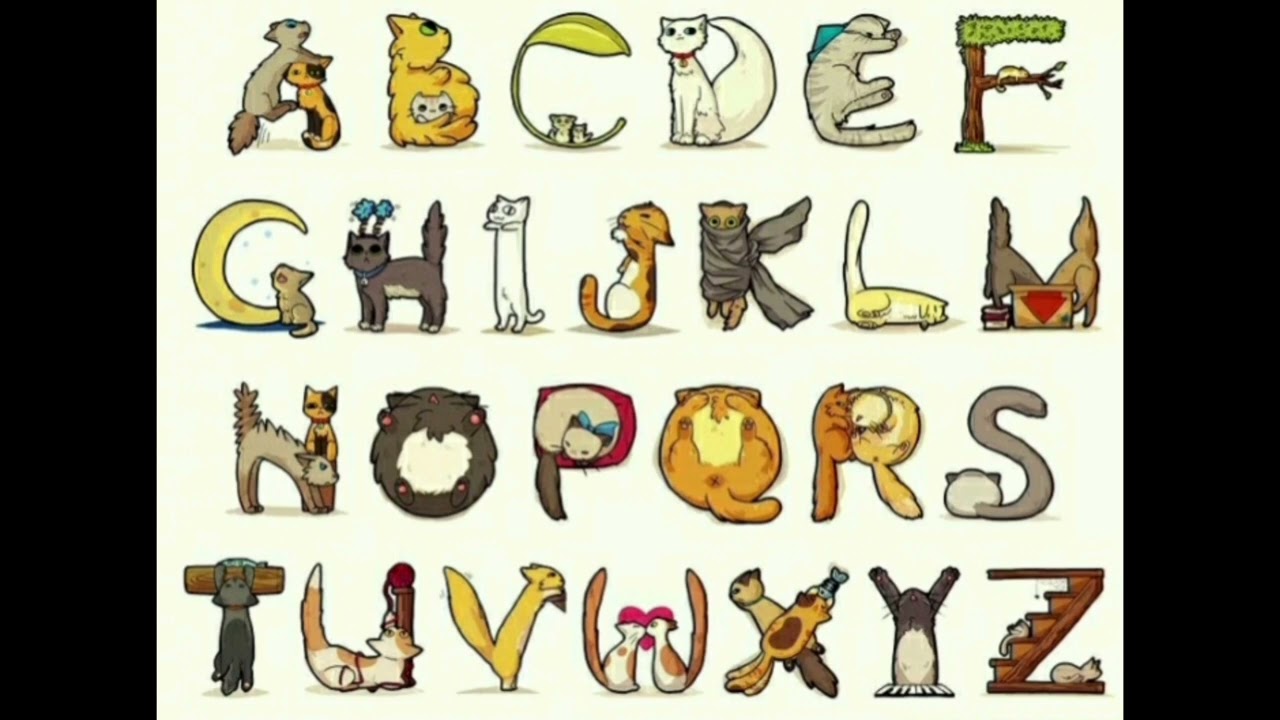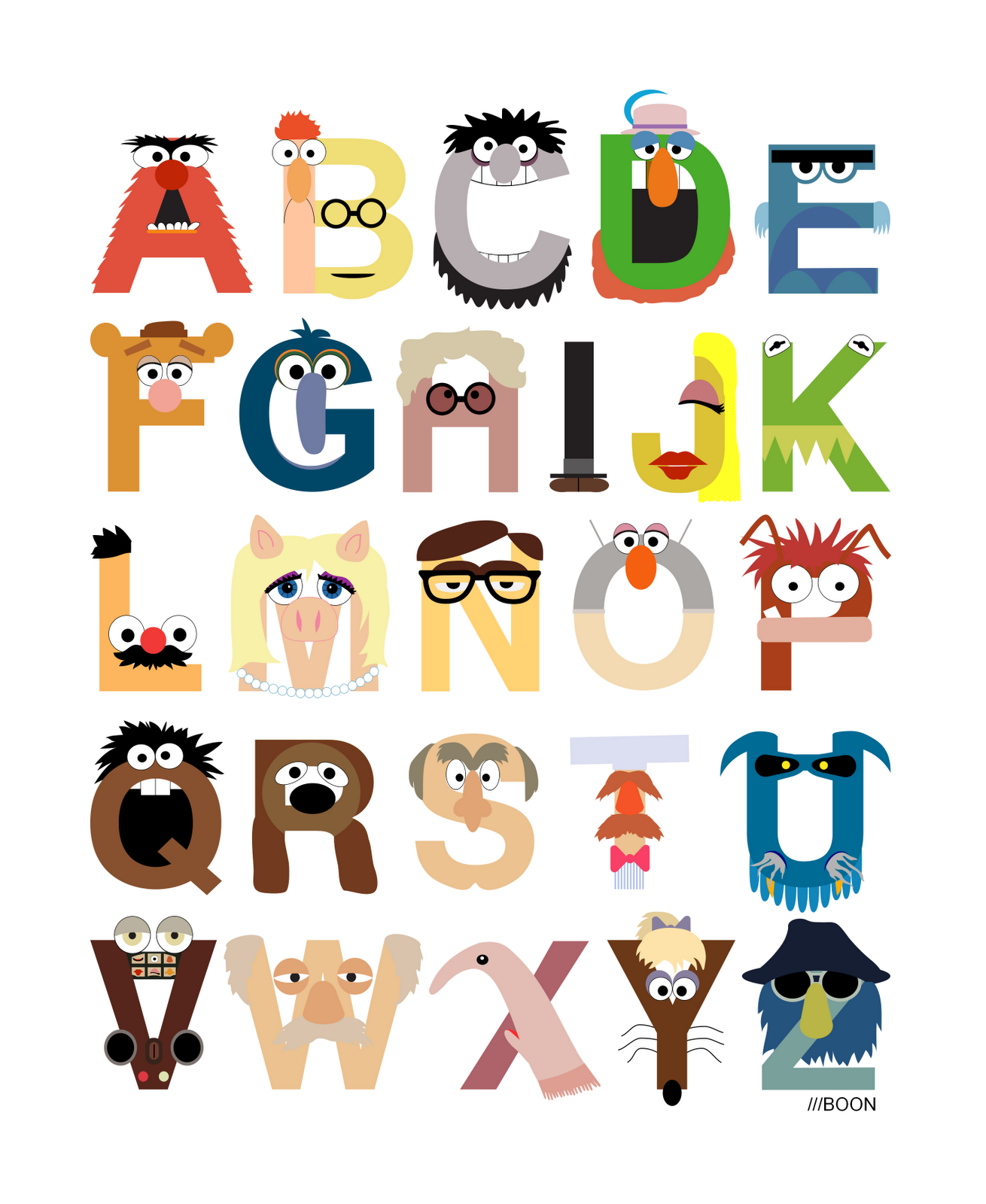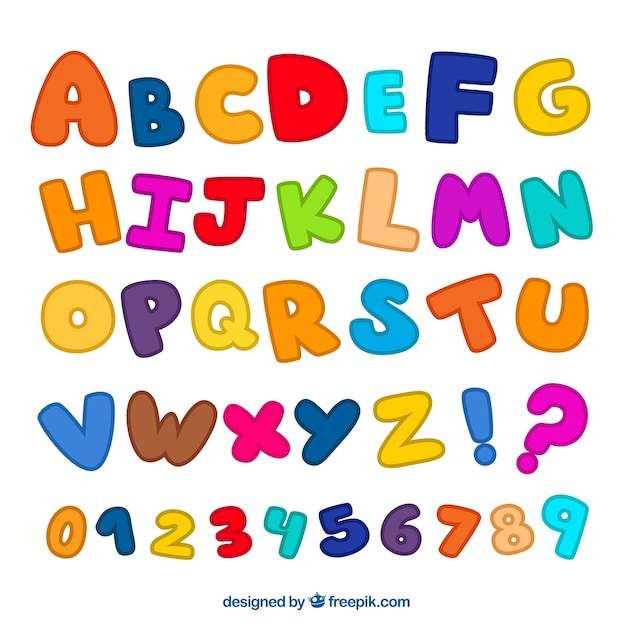
Что такое История забавных шрифтов?С целью добавить забавный штрих в печатный дизайн, забавные шрифты появились в начале 19 века.00с. Комические шрифты были первыми разработанными шрифтами, и они напоминали популярные комиксы. На протяжении 20-го века развивался графический дизайн, создавались более сложные шрифты, и они до сих пор имеют большое значение.
На что следует обратить внимание при выборе шрифта Fun? Веселые шрифты следует выбирать с учетом сообщения, которое вы хотите передать.